虽然“地摊经济”的到来,很多人都纷纷涌向街头,开启了自己的摆摊生活,甚至有不少的书法家或者书法爱好者们也在街头秀上一把,分得“地摊经济”的一杯羹,不仅如此,就连机器人“书法家”的出现在了街头,书写不输书法家,提按使转,动作干净利落,笔笔到位,字字皆法,颠覆你的审美,围观的人很多,甚至还有不少购买,看来机器人“书法家”很受热捧,就连很多小朋友也要凑凑热闹,很多人就开始有了担心,既然机器人“书法家”现街头了,真正的书法家要失业了?这个问题也困扰着不少人,对此你怎么看?分享你的看法。
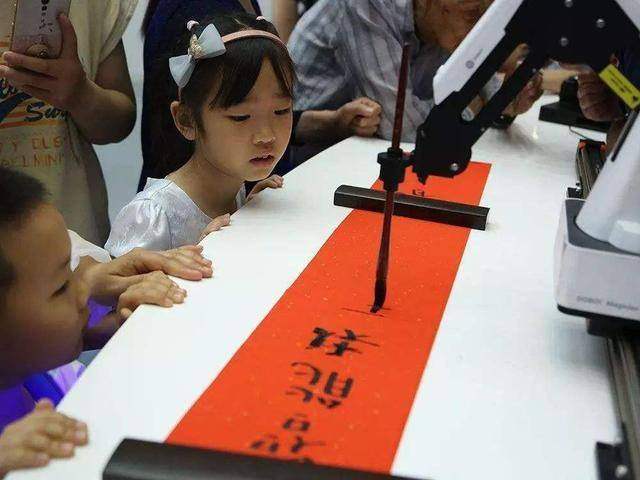
随着人工智能的不断深入发展,现在已经渗透于各种各样的职业中,我们以前见过机器人运动员,搞起足球比赛,也见过机器人“服务员”,工厂里见过机器手等等,而还真没有见过机器人书法家,而这一次彻底颠覆了我们的认识,害怕的事情还真出现了,机器人写书法,很多人也是第一次听到,更是第一次看到,纷纷赶来围观,一探究竟。
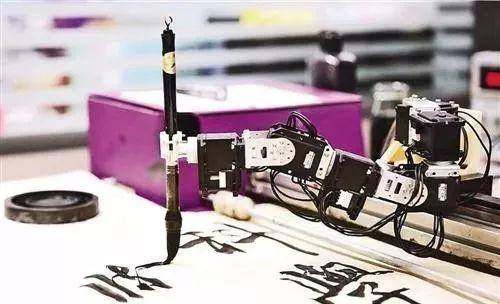
从现场书写的情况来看,只要给它设定好既定的程序,机器人“书法家”就会很精准地书写出来,而且和预设字体一模一样,肉眼根本无法区分,很多就说,机器人“书法家”就是王羲之在世,从这一句话中,我们也可以看出对机器人“书法家”的认可程度,众所周知,机器人是按照既定程序执行,在用笔上无法体会到真正的那种跌宕起伏,也无法感受到书法的真正妙处,书法是一门古老的传统的艺术形式,它不仅仅包含书写的过程,也是一个文化涵养的问题,书法家通过书写可以反映个人的情绪,认知,甚至是涵养修为,而这些机器人即使能够写得再好,也无法体会到,这也是机器人“书法家”和真正的书法家之间的根本区别。
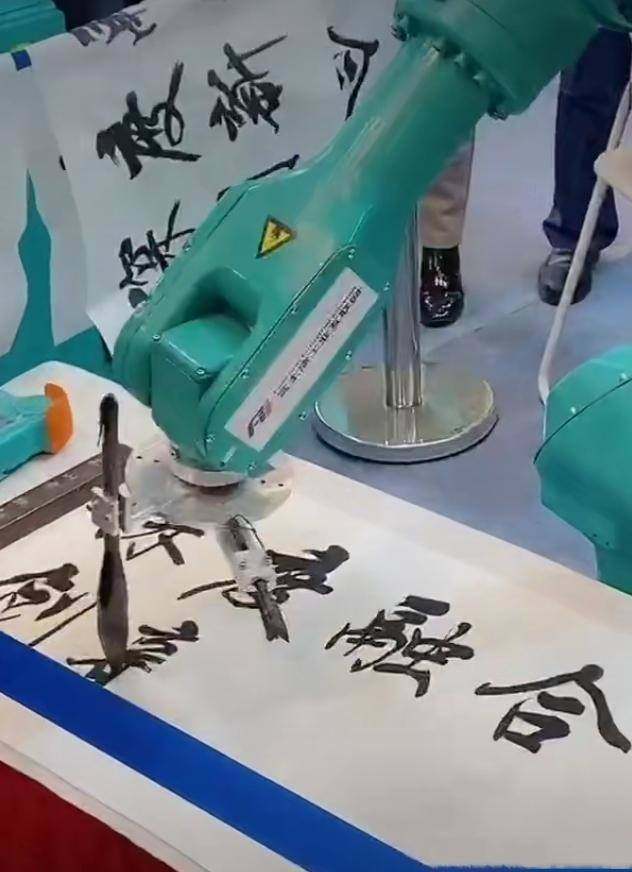
基于此的认识,笔者认为,机器人“书法家”根本不会取代书法家,这一点是可以肯定的,其实话又说过来,人工智能发展是好事,也不能够在任何领域都要掺和一把。